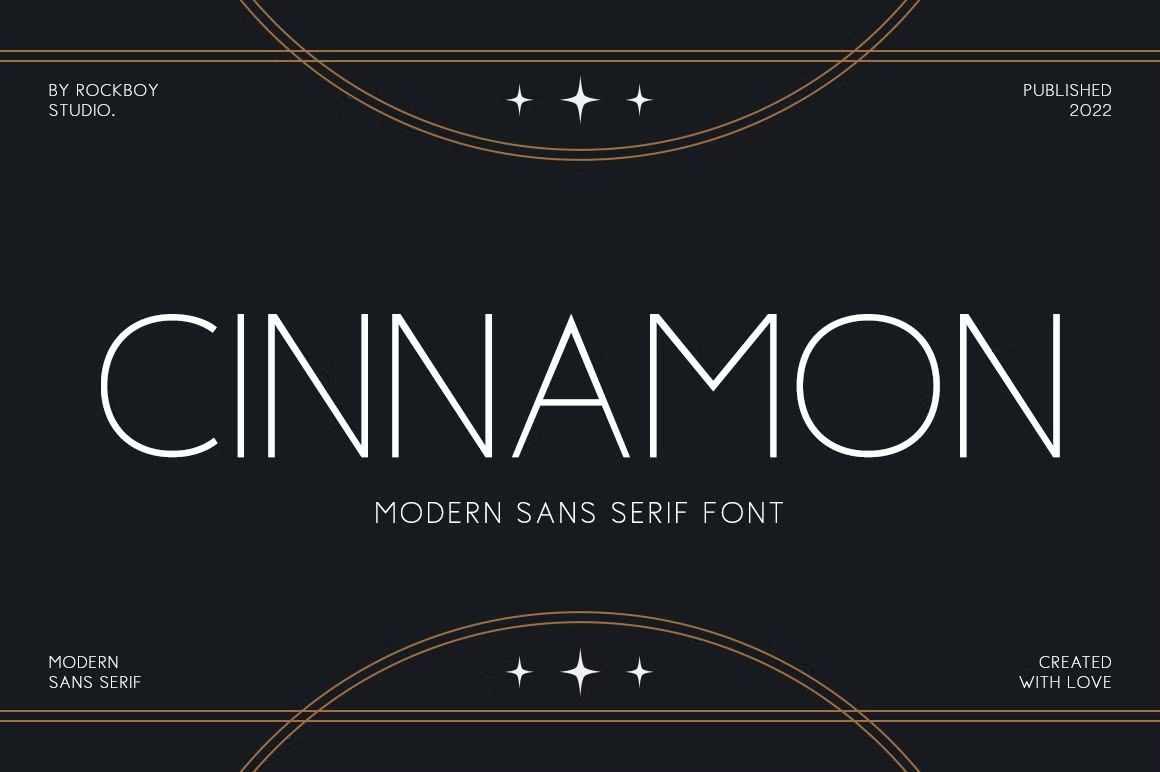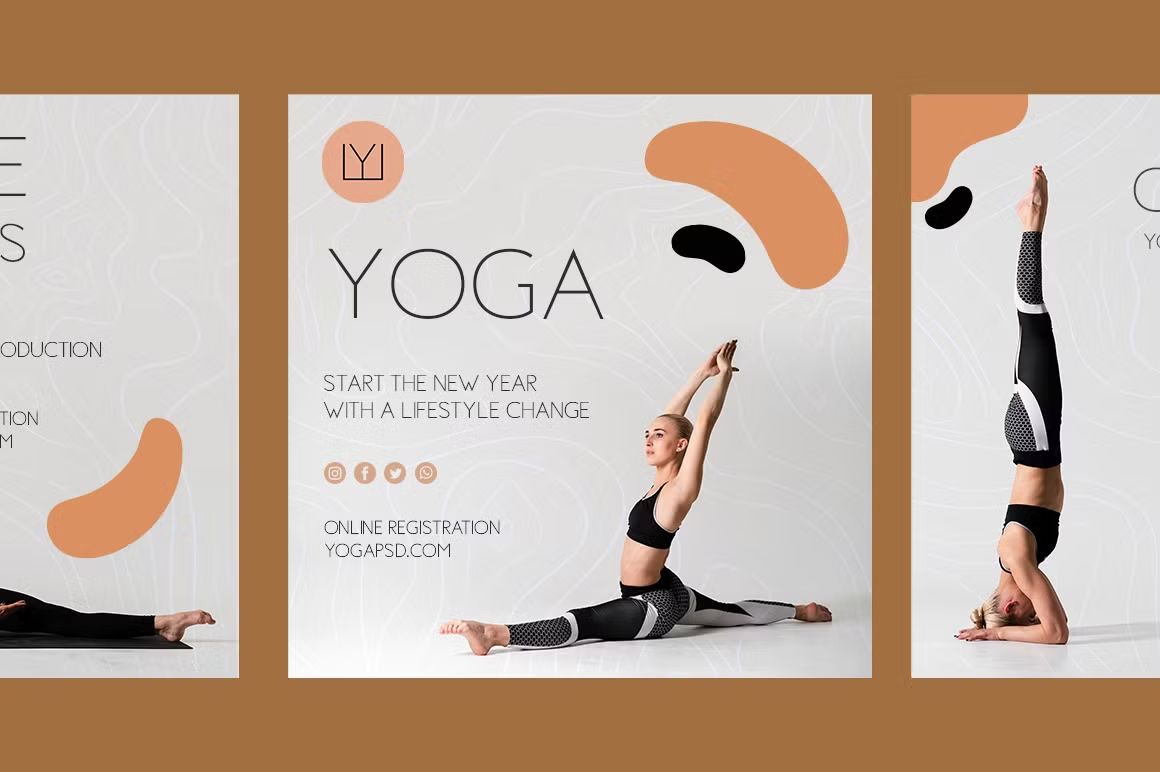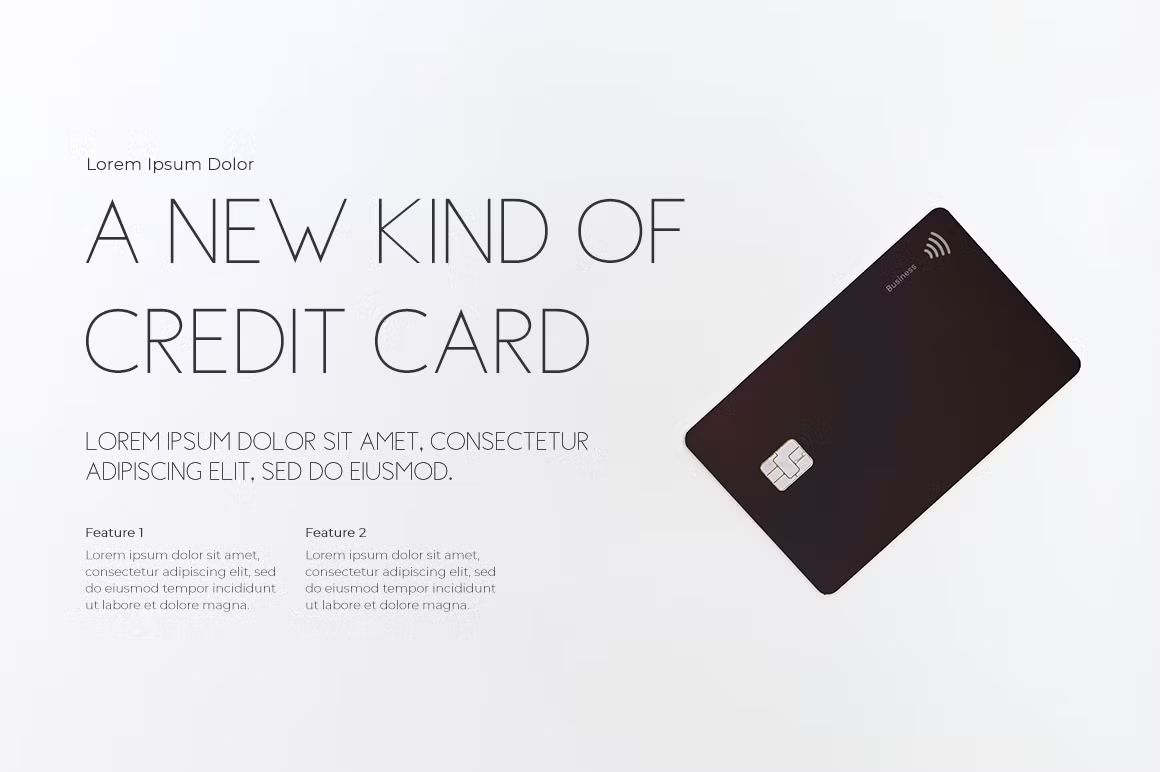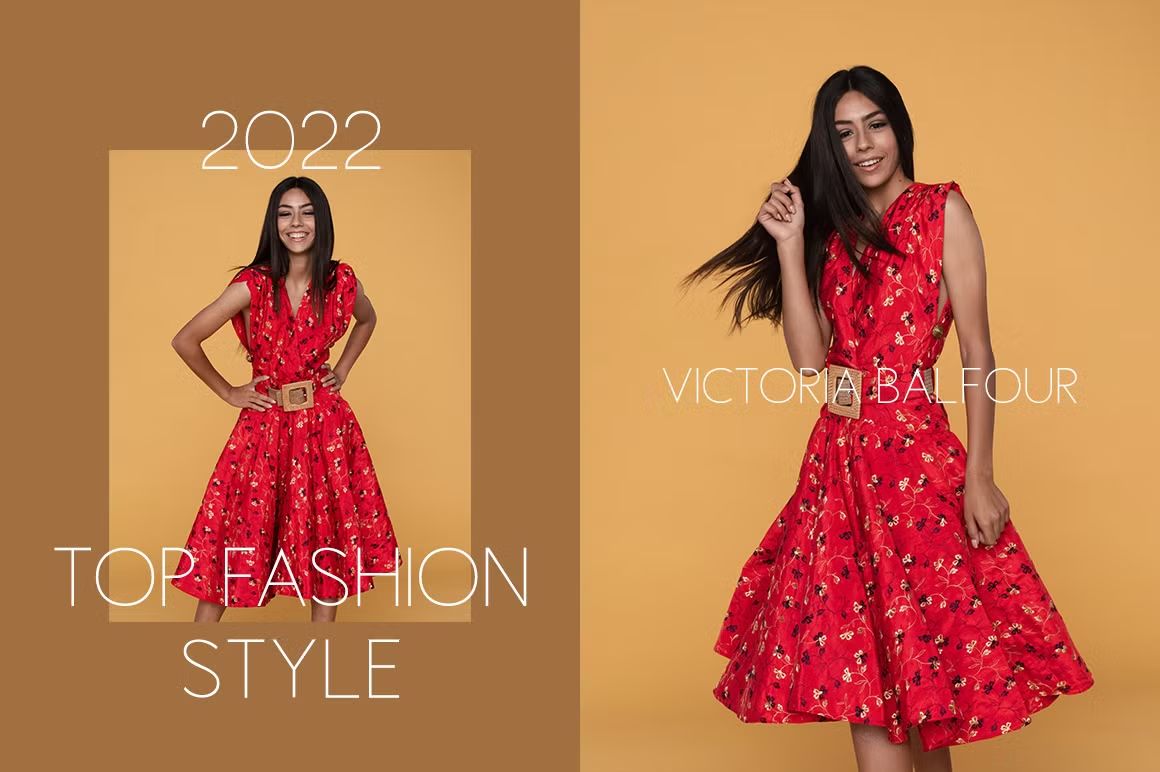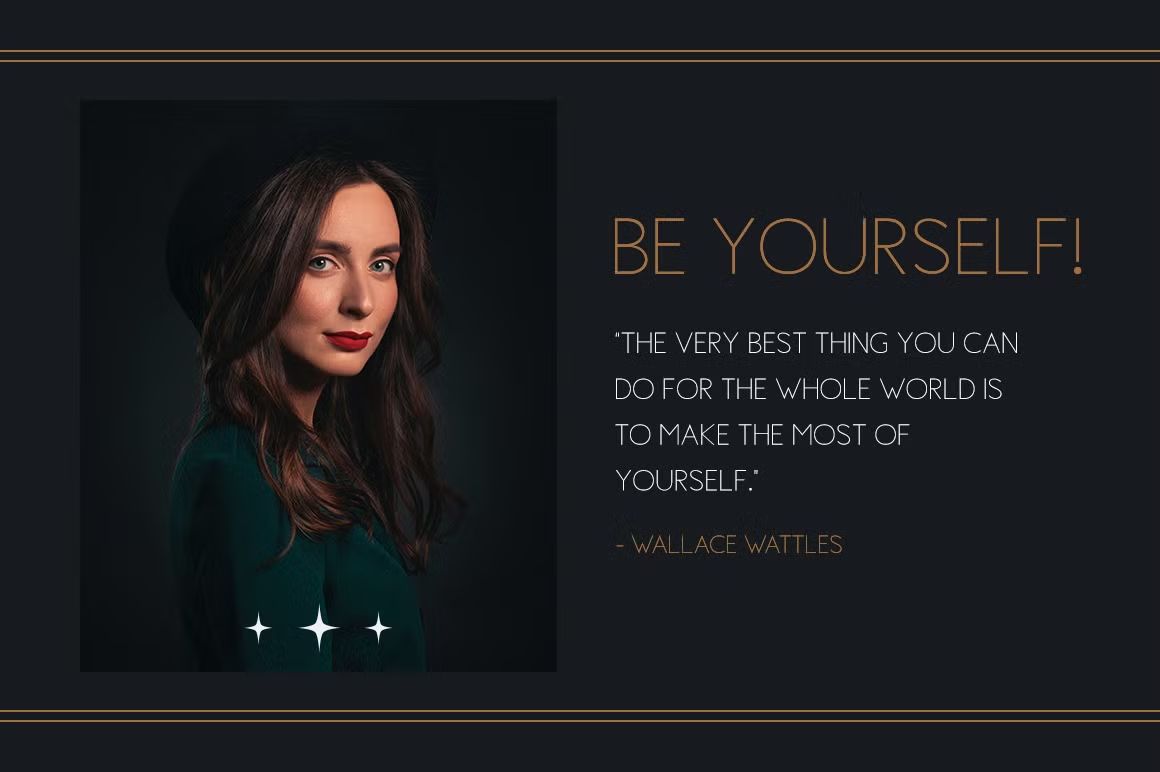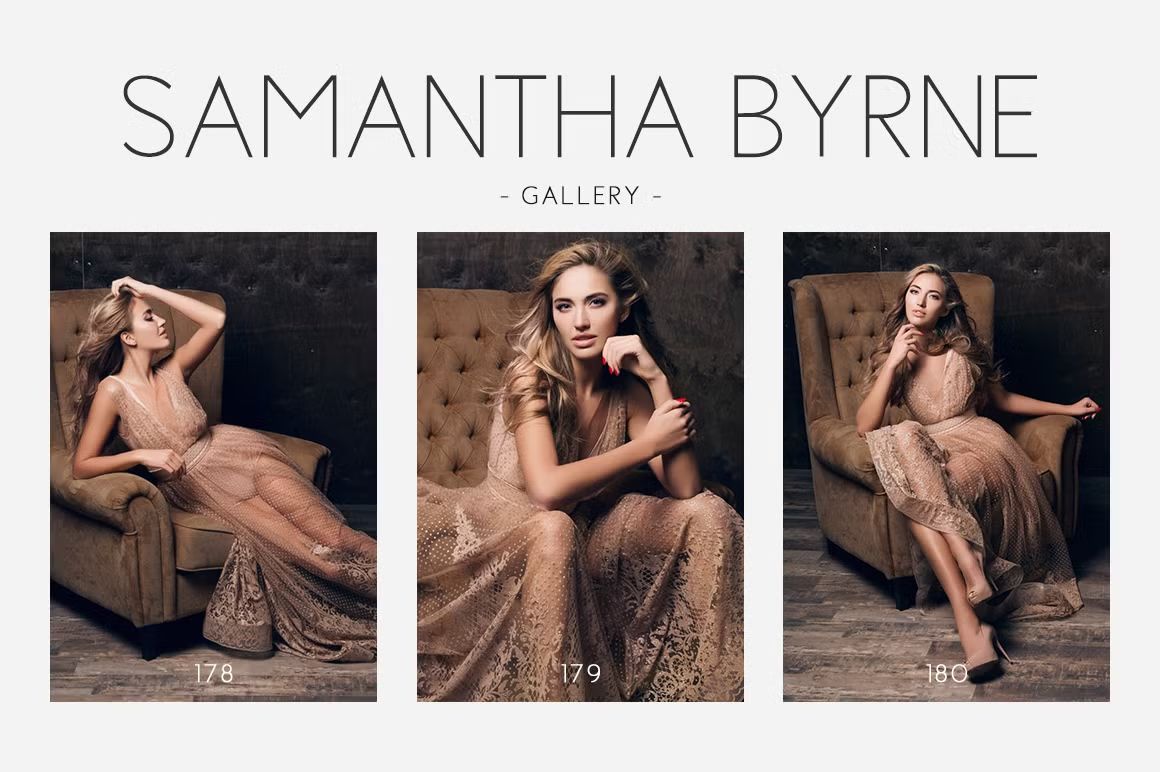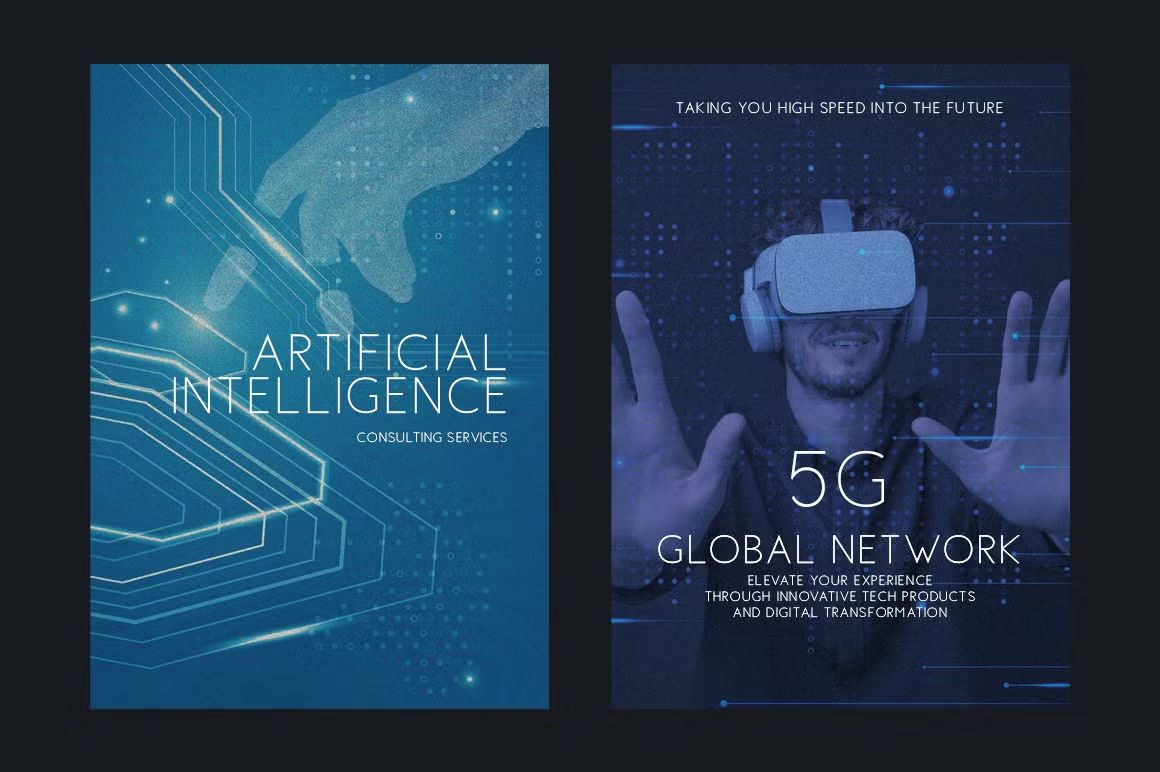
Cinnamon – Sans Serif Font
Cinnamon adalah font sans serif lembut dan bersahabat, cocok untuk branding makanan, kemasan, dan desain modern. Format OTF/TTF/WOFF, siap digunakan.
Cinnamon adalah font sans serif dengan gaya modern yang lembut dan bersahabat. Memiliki bentuk huruf yang membulat dan proporsi yang seimbang, font ini cocok untuk branding, desain produk makanan & minuman, kemasan, media sosial, dan proyek kreatif lainnya. Cinnamon memberikan kesan hangat, ramah, dan tetap profesional dalam setiap desain.
• Sans serif modern dengan ujung membulat yang lembut
• Ideal untuk branding, packaging, dan desain kreatif
• Termasuk huruf kapital, kecil, angka, dan simbol